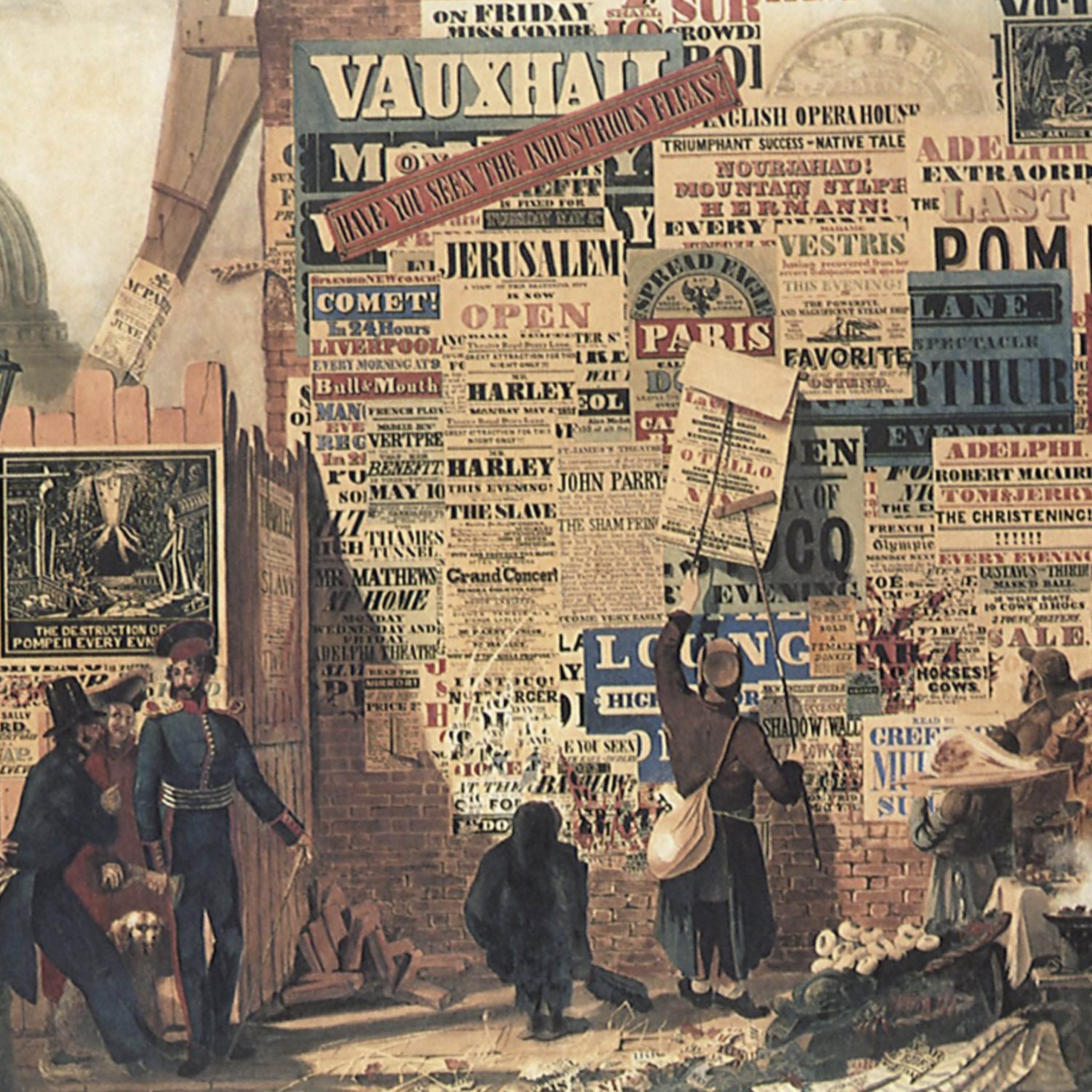
Storia del manifesto
Facciamoci caso: il termine manifesto rivela la funzione dello stampato: “manifestare”. Nasce in Europa nel XVII secolo, inizialmente come strumento informativo, spesso utilizzato per proclamazioni ufficiali o eventi religiosi. Con l’invenzione della stampa tipografica, si diffuse rapidamente, ma fu nel XIX secolo, con la litografia, che il manifesto assunse la forma moderna: un mezzo visivo capace di combinare testo e immagini. Durante la Belle Époque (fine ‘800), grazie ad artisti come Jules Chéret in Francia, il manifesto divenne un’opera d’arte, legando la pubblicità alla cultura visiva. In questo periodo venne utilizzato principalmente per promuovere spettacoli teatrali, prodotti di consumo e mostre. Nel XX secolo, il manifesto fu influenzato dalle avanguardie artistiche, come il Futurismo in Italia, il Costruttivismo in Russia e il Bauhaus in Germania, che sperimentarono con colori audaci, tipografie innovative e messaggi dinamici. Durante le guerre mondiali, divenne uno strumento di propaganda politica, mentre nel dopoguerra continuò a evolversi come mezzo pubblicitario e artistico. Oggi, il manifesto rimane un simbolo della comunicazione visiva, adattandosi ai contesti culturali e tecnologici contemporanei.